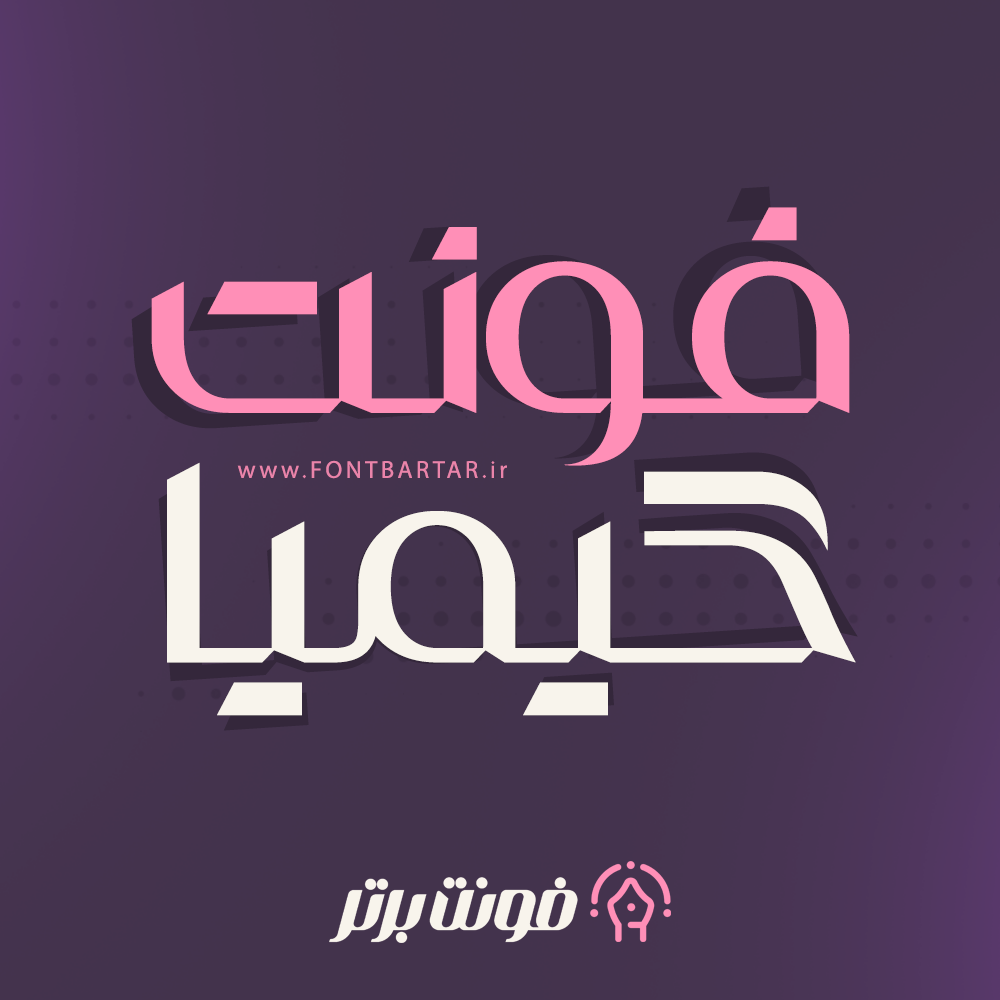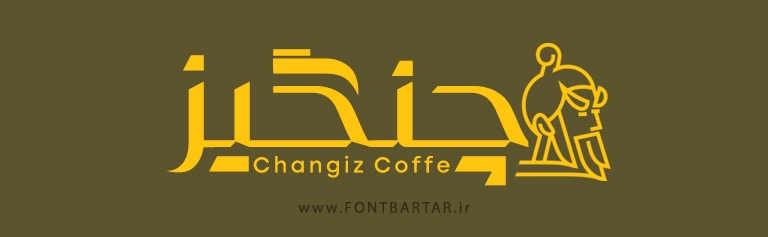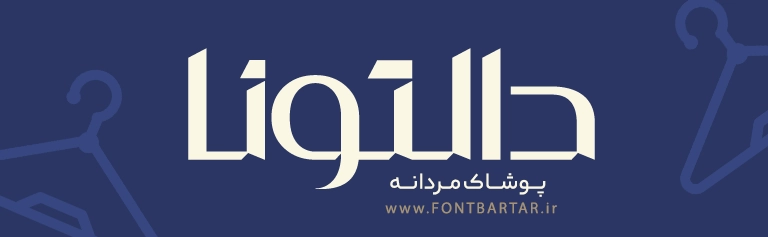
Kimia Font
دانلود فونت کیمیا – فونت فارسی خاص و مدرن برای طراحی حرفه‌ای
فونت جدید کیمیا (Kimia Font) یکی از خاص‌ترین و جدیدترین فونت‌های فارسی مدرن است که توسط تیم فونت برتر (FontBartAr.ir) طراحی شده است. این فونت جدید فارسی با ترکیبی از ظرافت، ساختار هندسی و خوانایی بالا، گزینه‌ای فوق‌العاده برای طراحی‌های دیجیتال، لوگو، پوستر، بنر تبلیغاتی و رابط کاربری (UI/UX) به شمار می‌رود. خرید فونت جدید با الهام از سبک‌های آینده‌نگر و طراحی فانتزی ساخته شده و به طراحان اجازه می‌دهد در عین سادگی، حس قدرت و مدرن بودن را در آثار خود القا کنند.
ویژگی‌های فونت فارسی کیمیا
• طراحی خاص و منحصربه‌فرد با استایل هندسی
• مناسب برای طراحی پوستر، لوگو، بنر و رابط کاربری
• دارای وزن متعادل و حروف نرم و چشم‌نواز
• پشتیبانی از حروف فارسی و عربی به‌صورت کامل
کاربرد فونت کیمیا در طراحی
فونت کیمیا یکی از بهترین فونت های جدید انتخاب‌های محبوب طراحان مدرن است.
از این فونت می‌توان در موارد زیر استفاده کرد:
• طراحی لوگوهای خلاقانه و خاص
• ساخت پوسترهای تبلیغاتی چشم‌گیر
• طراحی کاور موزیک و پست شبکه‌های اجتماعی
• تایپوگرافی هنری برای برندهای مدرن
• رابط کاربری نرم‌افزار و وب‌سایت
۱. فونت کیمیا برای چه نوع طراحی مناسب است؟
این فونت برای طراحی‌های گرافیکی مدرن، لوگو، پوستر و پروژه‌های دیجیتال بسیار مناسب است.